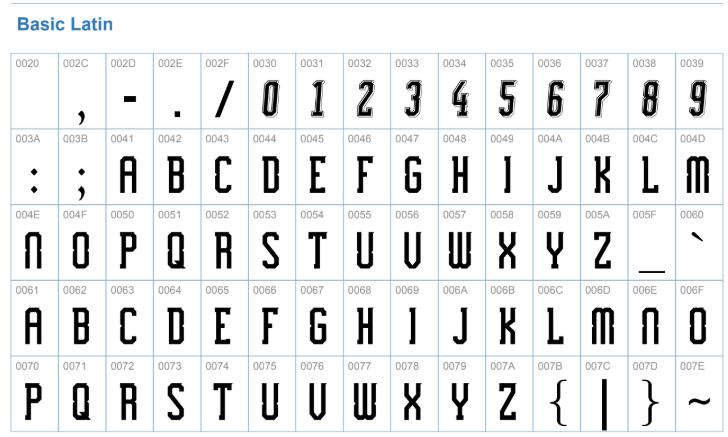
A temporada 2026 do Club Atlético Peñarol chega carregada de expectativas, e a identidade visual do Manya não fica para trás. Além dos novos uniformes, um dos elementos mais aguardados por designers e torcedores é a tipografia oficial que vai estampar os nomes e números nas costas dos jogadores.
- Peso: Regular, com glifos numéricos e alfabéticos completos
Estilo visual da tipografia
A tipografia Peñarol 2026 aposta em um desenho geométrico e levemente condensado, com traços retos e cantos angulosos que remetem à garra do time carbonero. Os números, em especial, possuem acabamento moderno e recortes estratégicos que garantem excelente legibilidade tanto no estádio quanto nas transmissões em TV e telas de dispositivos móveis.
O estilo conversa diretamente com a história aurinegra, mas sem abrir mão da contemporaneidade — as hastes são firmes, os espaçamentos equilibrados e a fonte se mantém limpa até mesmo em tamanhos reduzidos, facilitando aplicações em materiais impressos e digitais.
Aplicação no uniforme
No uniforme titular, com as tradicionais listras amarelas e pretas, os números aplicados em preto com contorno fino mantêm contraste total. Já no uniforme reserva, predominantemente escuro, a fonte ganha vida em amarelo vibrante, criando um impacto visual enorme.
Caso o terceiro uniforme da temporada 2026 entre em campo, a tipografia se adapta em branco ou detalhes vazados, mantendo a unidade do conjunto aurinegro.